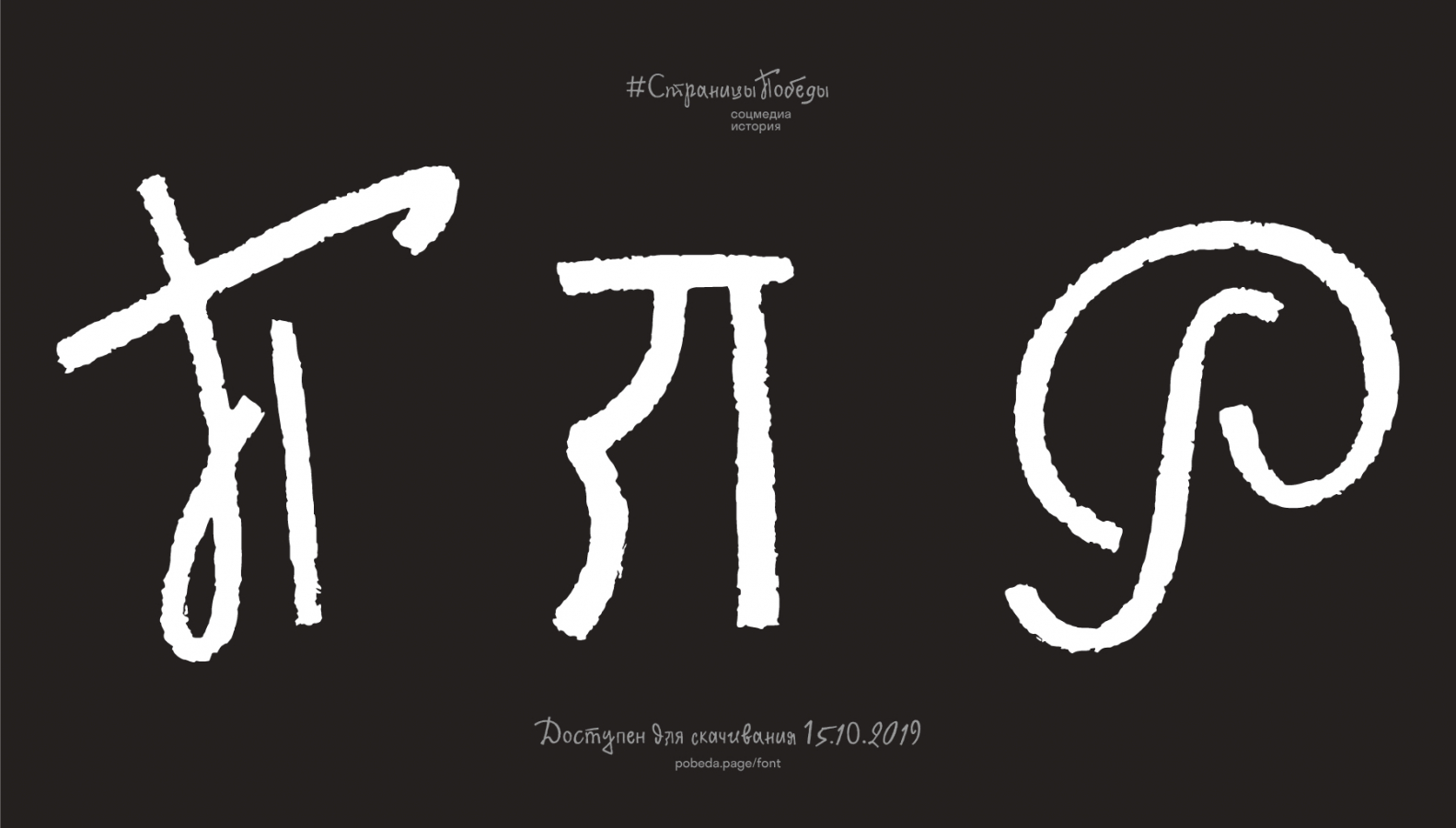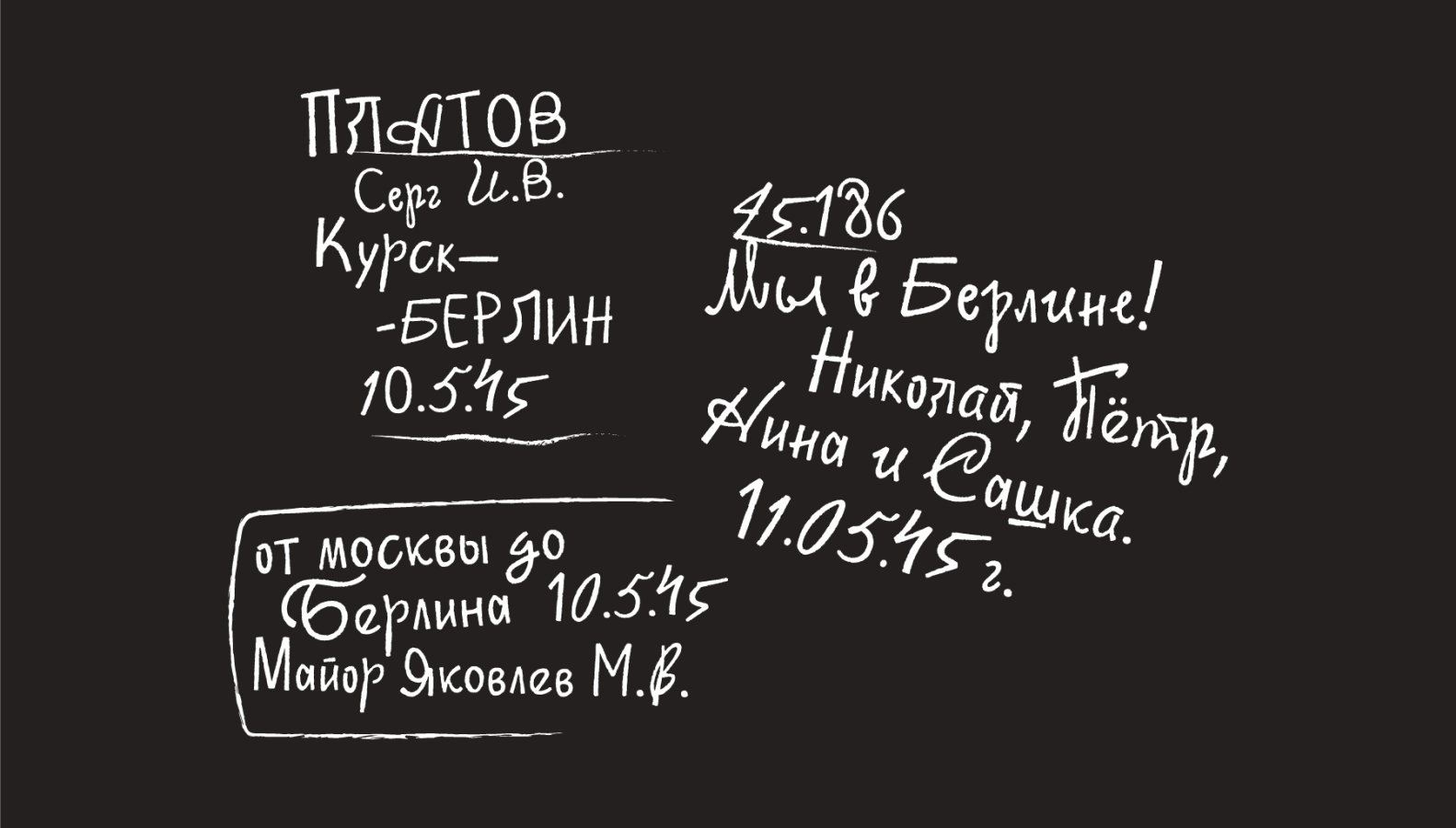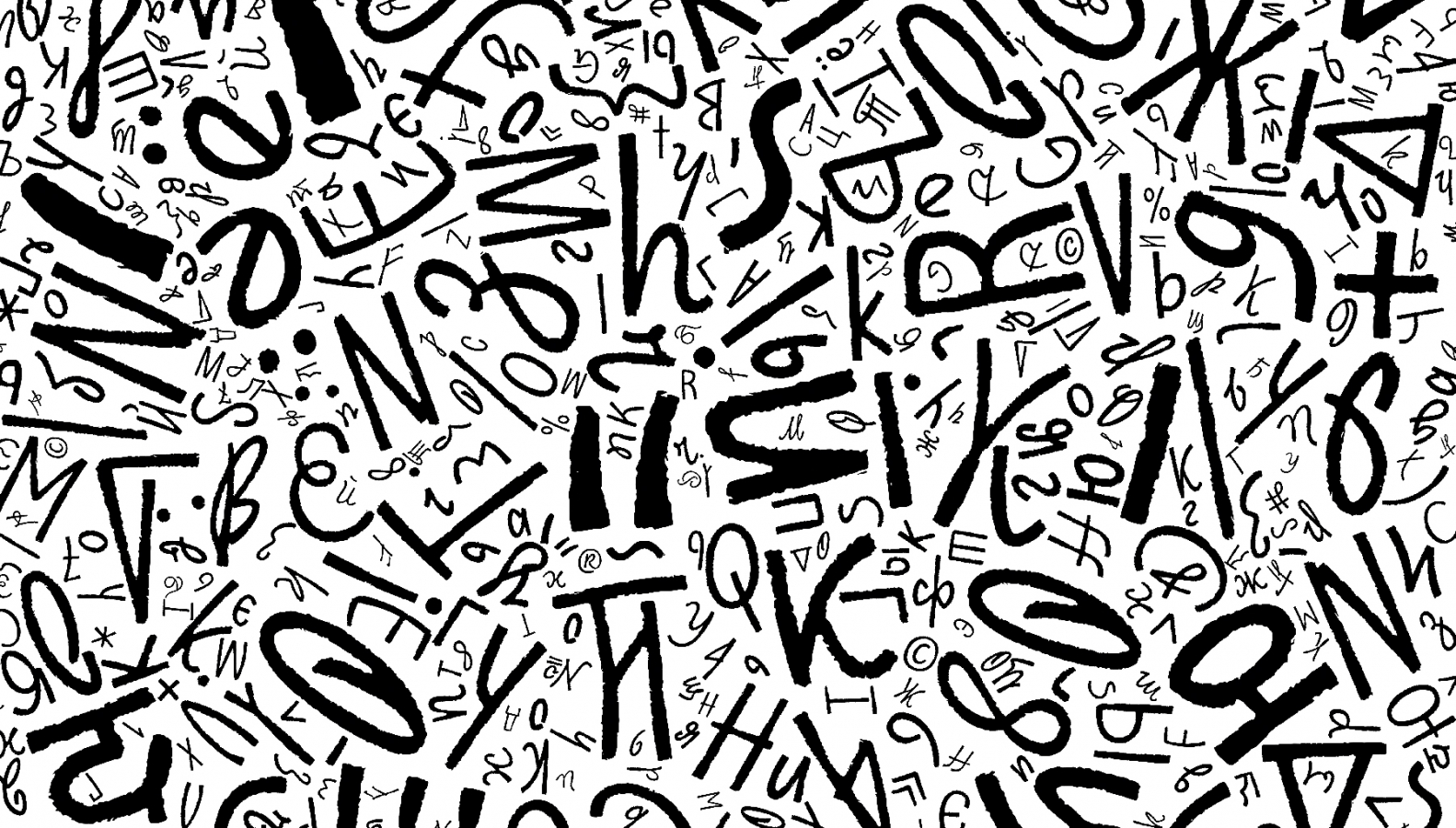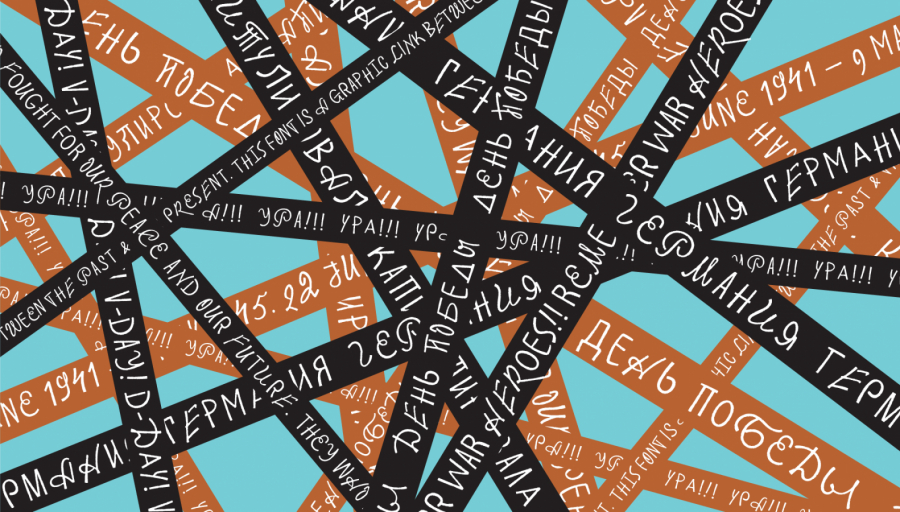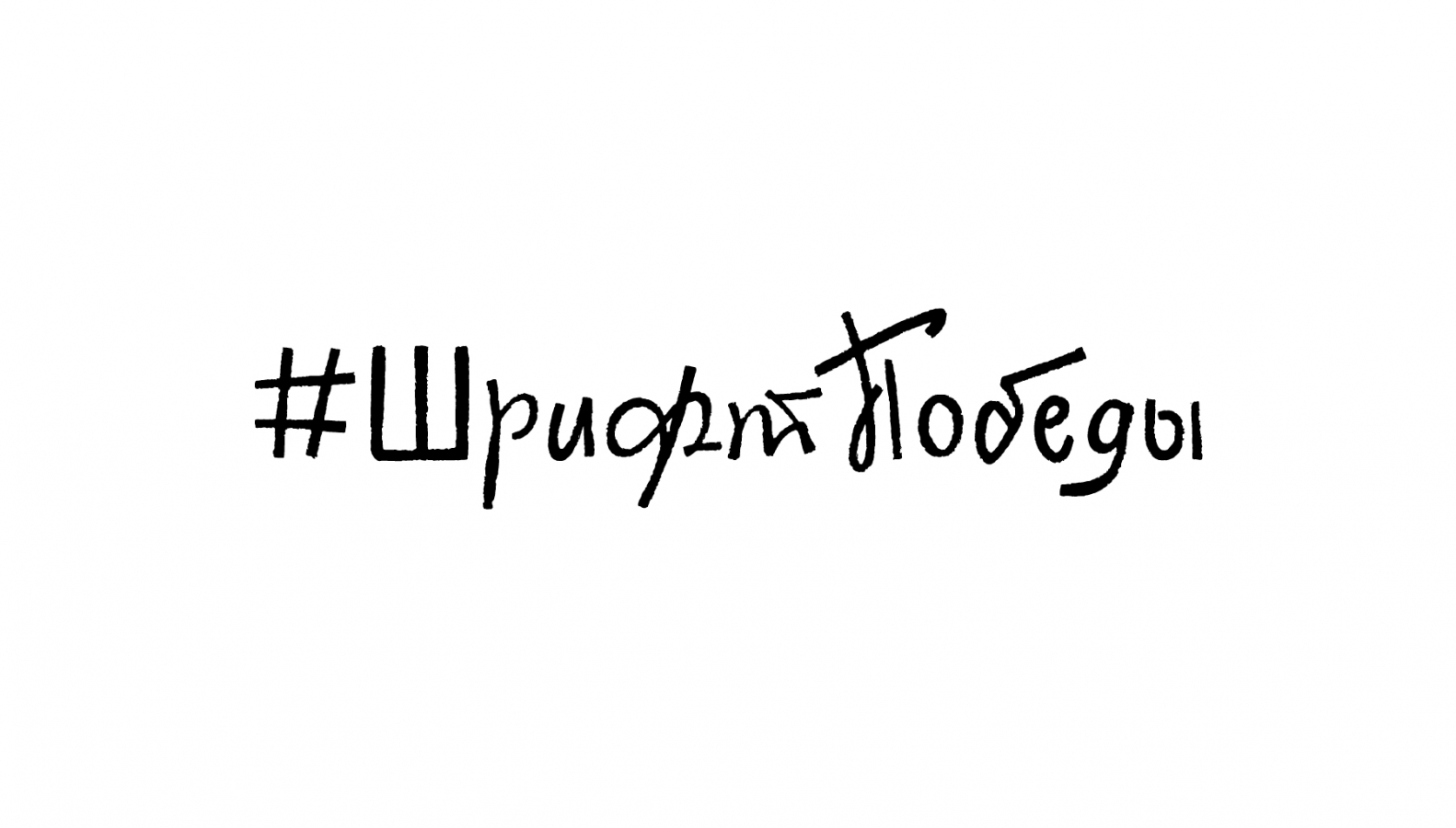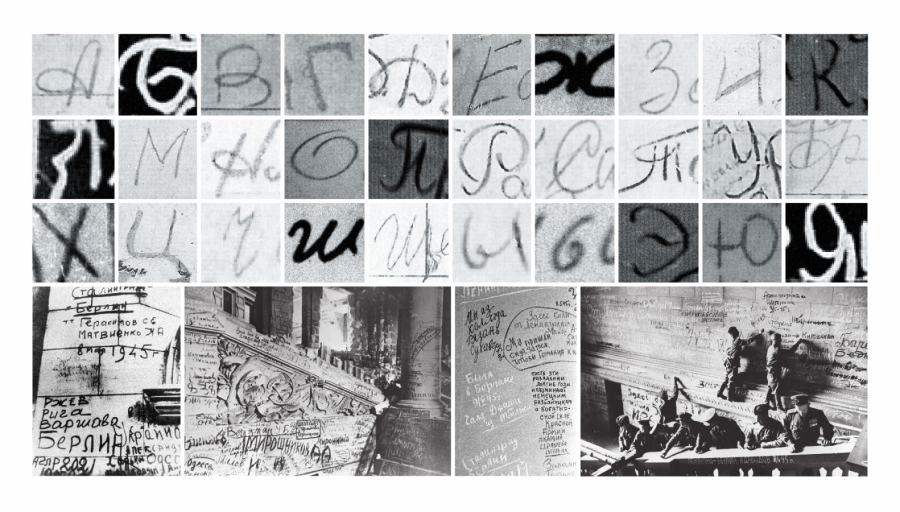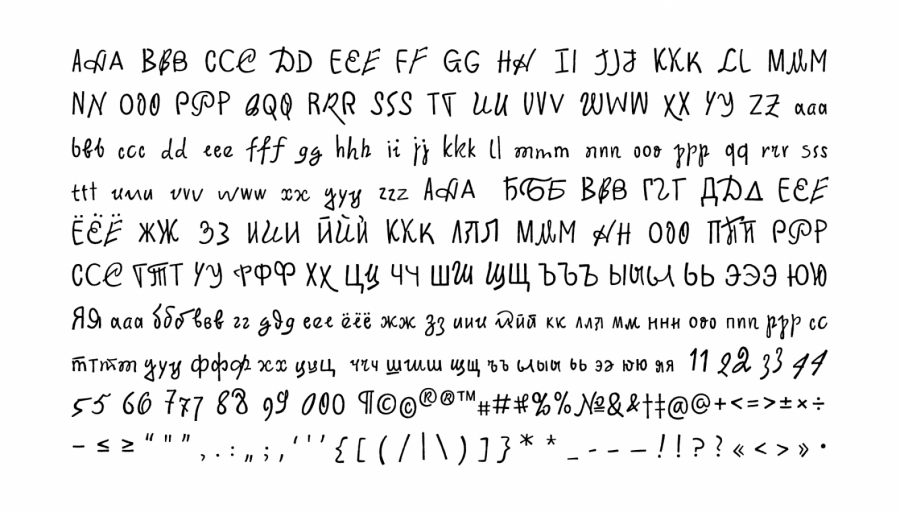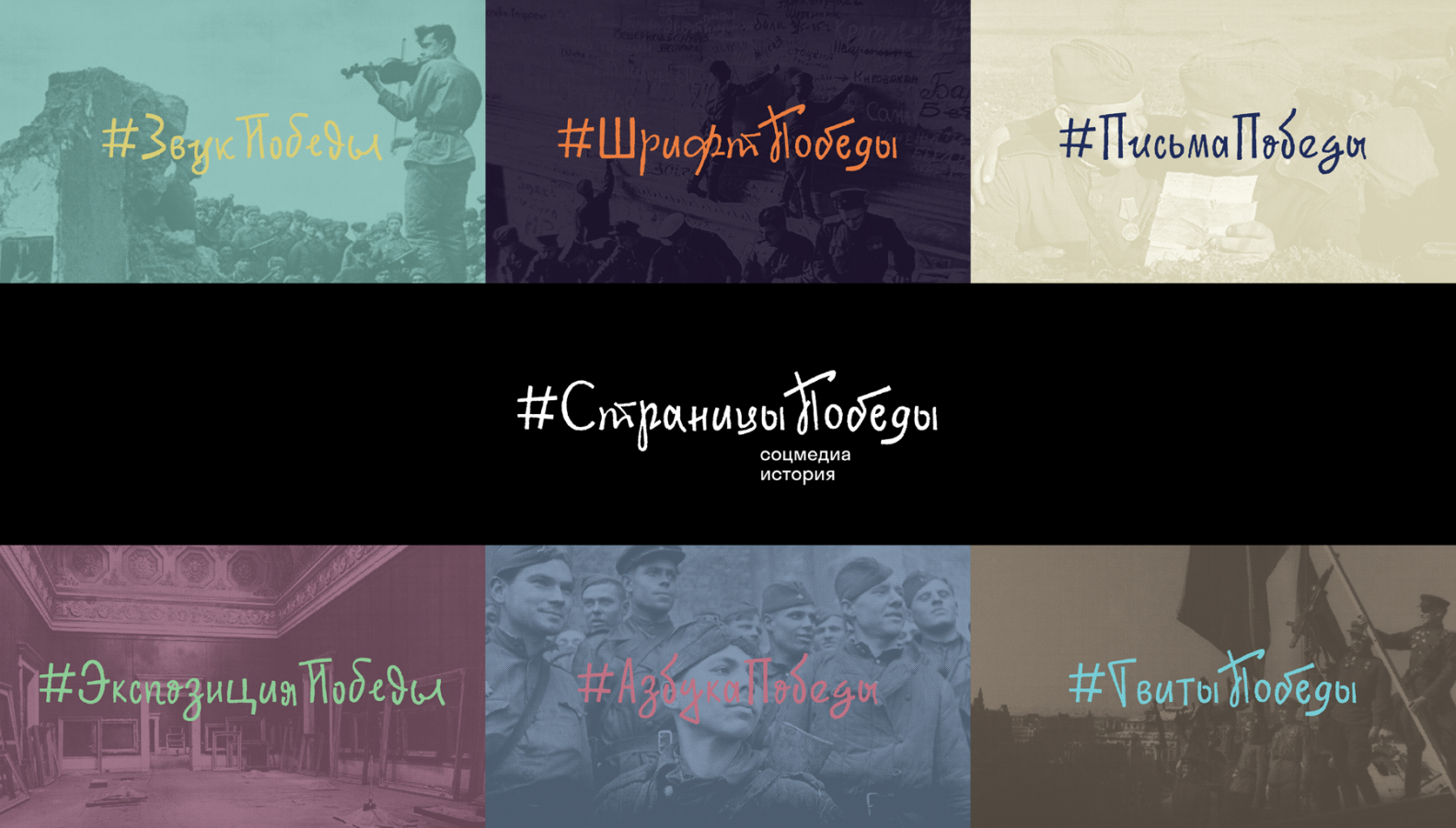
RT запустит спецпроект к 75-летию Победы — для него создан динамический шрифт «Май»
Прообразом букв стали реальные символы, начертанные руками советских солдат
Весной 1945 г. советские солдаты оставили сотни надписей на стенах Рейхстага в Берлине. Это были слова, полные радости победы и горечи потерь: «За кровь земляков…», «Из Сталинграда вошёл в Берлин», «За налёты на Москву, за обстрел Ленинграда». В преддверии 75-летия окончания Великой отечественной войны RT создал «живой» шрифт на основе рукописных граффити Рейхстага.
Шрифтом «Май» RT открывает свой масштабный проект, посвящённый грядущему 75-летию победы СССР в Великой отечественной войне — #СтраницыПобеды. Создатели #1917LIVE и #Romanovs100 рассмотрят историю Великой отечественной войны сквозь призму социальных медиа и digital art.
Запуск основной части проекта состоится в январе 2020 г., но креаторы уже сейчас опубликовали уникальный шрифт, который будет везде его сопровождать. Он разработан совместно с дизайн-студией Contrast Foundry. Прообразом каждой буквы стали реальные символы, начертанные руками советских солдат 75 лет назад.
Кирилл Карнович-Валуа, автор идеи проекта:
В этих надписях — голоса победителей, их слова и почерк, их память. Своими рукописными буквами и знаками, каллиграфическими и неотёсанными, аккуратно выведенными и экспрессивно-резкими, шрифт „Май‟ создает графическую связь между прошлым и настоящим, между героями Победы и нами, их потомками.
Каждая буква имеет несколько альтернативных форм, а сами буквы располагаются в строчках немного неровно, что отражает естественность рукописного начертания слов на стене.
Дизайн-студия Contrast Foundry:
В крупном размере хорошо видна текстура, как будто буквы были написаны на шершавой поверхности. В мелком же кегле фактура едва заметна, от неё остаётся лишь лёгкая мягкость набора. Этого эффекта нам удалось добиться путём написания алгоритма, который модифицировал контур букв. Он не просто механически деформировал его и сделал „рваным‟, а позволил подчеркнуть живое и естественное ощущение, которое создаётся благодаря шрифту.
Кирилл Карнович-Валуа, автор идеи проекта:
У шрифта очень много характеров — в нём много необычных акцентных букв, которые мы взяли со стен Рейхстага, но есть и много спокойных, классических написаний. Благодаря вариативности, благодаря альтернативным формам, любое слово или фраза может иметь несколько совершенно разных начертаний. Они могут быть аккуратными и спокойными в прописи, могут быть строгими и лаконичными при выборе заглавных печатных букв, а могут быть броским и яркими, если все заглавные буквы сделать акцентными.
Эта вариативность, с одной стороны, заключает в себе то многоголосие солдатских посланий, характеров, судеб, личностей, которое какое-то время хранили стены Рейхстага. А с другой — даёт возможность каждому из нас спустя 75 лет составить свою уникальную фразу из этих написаний. Сказать спасибо, отдать дань памяти, создать жизнеутверждающее или антивоенное послание.
Шрифт Победы «Май» — это своего рода живой графический памятник ветеранам. Но мы хотим верить, что в этих оживших буквах нами заложено и напоминание, какой ценой была одержана та Победа. Помня и зная, через какой ад, боль и страдания прошёл мир в середине ХХ века, мы — молодое поколение, наследники той Победы — должны сделать всё, чтобы люди больше никогда не узнали, что такое мировая война.